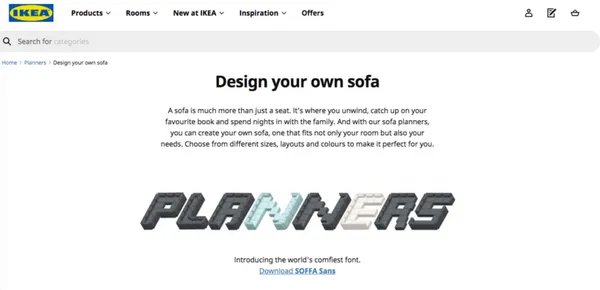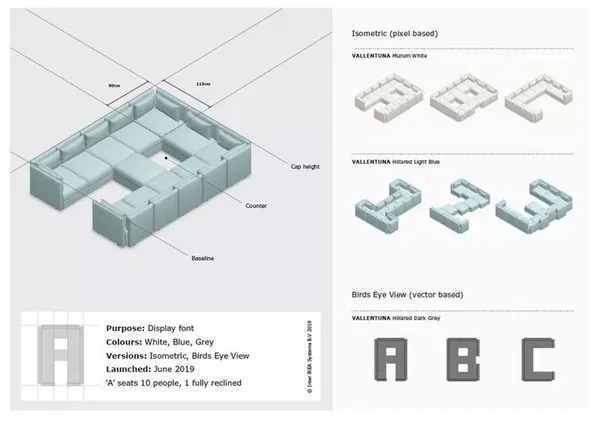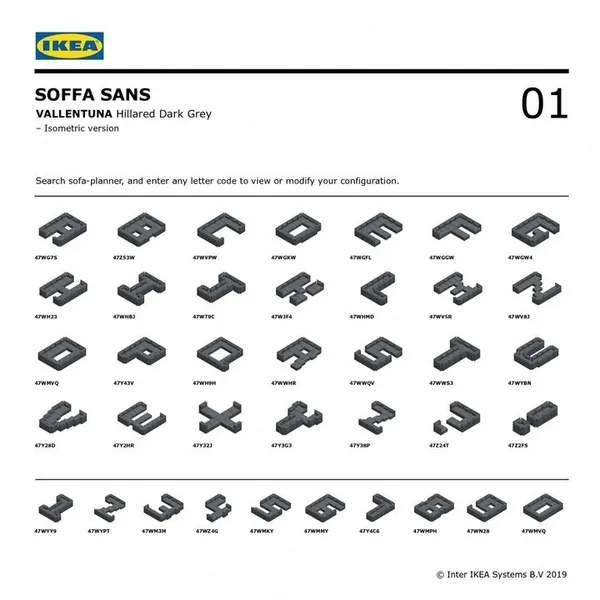
IKEA推出一套「世界上最舒服的字體」
這套字體起名為「Soffa Sans」,因為它的靈感正是來自沙發。
Soffa Sans
事情要從IKEA前不久推出的線上沙發搭建工具 Vallentuna 說起。定制傢俱雖然不是什麼新鮮事物,但能夠讓顧客利用線上親手設計的就不多見了,於是Vallentuna上線後相當受歡迎,不管有沒有預算,民眾都可以享受成為一名沙發設計家的獨特體驗。
Soffa Sans
國外網友們紛紛貢獻出了自己的創意,在一眾新意十足的設計中,以字母和短語的設計最為常見,受此啟發,IKEA乾脆找來英國的Proximity London公司合作,把網友們的設計做成了這套「世界上最舒服的字體」Soffa Sans。
Soffa Sans
「模組化的形狀和寬鬆的字母間距令它成為最通用的字體之一,我們期待看到它被使用。」英國和愛爾蘭的IKEA銷售負責人Marcos Tejedor 如此表示。